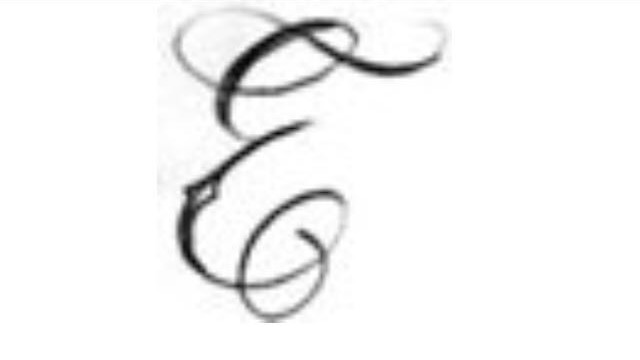
Welche Schriftart könnte das sein?
1. dürfte dies höchst wahrscheinlich handgeschrieben sein.
2. sollte ein Tattoo-Künstler so etwas auch von Hand schreiben (bzw. vorzeichnen) können, schließlich muss er dies ja hinterher mit den "Zeichengerät" Tattoo-Maschine auch sauber auf die Haut bekommen. Wenn der das also schon auf Papier nicht zu Weg bekommt, solltest du dir einen auf Schrifttattoo spezialisierten Künstler suchen, auch wenn der teurer sein sollte, denn... (Beim Tattoo sollte man NIE auf den Preis gucken, und den billigsten nehmen. So wie die Haut vor dem Tattoo war, wird sie nämlich nie wieder!)
3. So ein Tattoo hat man, wenn es gut istr, für den Rest seines Lebens auf der Haut, oder
4. wenn es schlecht ist, ärgert man sich viele Jahre darüber, muss sich das entweder überstechen oder per Laser herausbrennen lassen, was dann aber mindestrens 10 mal so viel Weh tut - und auch kostet, wie das verpfuschte Tattoo.
5. letztlich eignen sich Satzschriften ohnehin schlecht als Tattoo-Vorlage, da diese ja für einen möglichst gradlinigen Schriftzug entworfen sind, die Haut aber hat Kurven, und an diese muss der Schriftzug angepasst werden.